《包豪斯ABC》 用设计重新解读字体的意境
包豪斯在现代平面设计、工业设计和建筑设计领域最广为人知,也被讨论最多、模仿最多、收藏最多、展出最多。
如果要用某种图像去概括包豪斯的基本样貌与成就,那就是方、圆与三角,它告诉我们可以通过理性的原则来解释世界和构建世界,这几乎是所有我们这些"后来人"的共识。
1923年,瓦西里·康定斯基提出了三个基础几何图形与三原色之间的普遍对应关系:动态的三角形本质上是黄色的,静态的正方形本质上是红色的,宁静的圆形本质上是蓝色的。
包豪斯从历史主义史观和传统形式的碎片中发掘出了视觉设计的基本"语法"。而这种"语法"的核心元素,过去是,将来也必然是——它的影响与其说体现在现存的几乎所有的包豪斯物质遗产中,即那种特有的几何化秩序的建筑、产品、服装、LOGO、版式与字体等,不如说它也同时根植于现代设计师和艺术家的审美意识和精神世界中,即一种几何化分解的观察视角,一种对复杂问题归纳、抽象、提炼的能力,一种对形式与意味引发的思考方向,一种视觉与心理的科学研究方法。
BAUHAUS
《包豪斯ABC》于1991年首次出版,由两位著名平面设计师艾伦·路普顿和J.艾伯特·米勒设计完成。
1991年是数码设计的开端之年,当时关于版式设计的各类新锐批评文章也正风起云涌。两位设计大师结合数字技术和手工技法制作了这本书,用Compugraphic电子排版系统编排各式字体,用热蜡、红宝石以及十几把X-Acto美工刀手工等完成了页面设计。
为完成本书,艾伦·路普顿和J.艾伯特·米勒倾注了许多心血,他们试图将批判性的文字与可互相参照的、流畅优美的版式结合起来,每一页文字都搭配了发人深省的版式, 以此引发大家对平面设计的不同思考与讨论。
1921—1923年,赫伯特·拜尔在包豪斯求学。1925年,沃尔特·格罗皮乌斯邀请他负责排字印刷工作坊。拜尔在开发"新版式"方面发挥了重要作用,这种版式使用非衬线字体、字重变化规则和系统化网格,创建了一种简洁的组合。拜尔希望将他的设计建立在永恒、客观的规律之上,从而超越短暂的文化幻想。风格和自我表现应该服从于几何的纯粹性和针对功能的要求。
1925年,拜尔设计出一种字体(非衬线字体),他称其为"通用字体"。"通用字体"不仅仅是一种字体,也是一种可打印、可手写的、完整的书写体系。它将罗马字体简化为简单的几何形状。对拜尔来说,罗马字体是基本的印刷体,所有后续风格都是从这些形式开发而来的。
上图绘于1938年,图中拜尔展示了字体变化的历史进程。通用字体的独特之处是从希腊字母α开始寻求变化,这说明拜尔打算揭示西方字体的基础,而不是发明新的字体。
拜尔认为,由于大多数铅字都是由机器制作的,没有必要模仿凿子的切割线,也没有必要模仿笔触的上细下粗。于是,通用字体使用宽度均匀的线条绘制而成,用几何图形来定义字形。
20世纪20年代,不同于设计师们专注于新视觉语言如何发挥政治潜力,企业将关注点转向形式的规律性和稳定性的前景,以便在视觉上更好地体现企业的权威。这种焦点的"转移"并不是抹去设计的原有含义,而是让设计为公司的理念服务。
1962年,保罗·兰德为美国广播公司(ABC)设计的标志,是大公司采用现代主义设计的典范。兰德使用了通用字体的变体,通过改良几何造型并重复使用圆形完成了变形。这种简洁、规范的字体形状,展现出规范、统一、稳定的企业权威感。
字体的含义还会随着它所处的历史阶段和文化背景的变化而改变。谢尔马耶夫和盖斯玛联合公司在为美孚公司设计的标识中,就巧妙地使用了曾经激进的"未来字体"的变体。在这个设计中,未来字体与众不同的字母 o 用红色标出,用几何完美性表示美孚公司的产品——石油(oil)。美孚的标志象征着"未来字体"所表达的意义上的转变:它曾经象征着对权威的挑战,现在则象征着企业的权威。
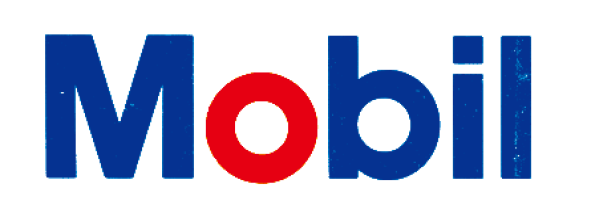
这种字体还被应用在热门电视剧《罗珊娜》的演职员表时,字体的几何形状和粗体设计,显然是要与这个有趣女人的自信、坦率和幽默相呼应。可是,这种表达与拜尔最初的设计意图相距甚远。
通用字体的出现是一种历史现象,它标志着19世纪的文化价值观的崩溃和一个新的、更加"理性"的世界的诞生。历史证明,字体的含义是不断更新的,不受形式的禁锢。例如,在第二次世界大战后,企业采用了不同的通用字体的变体,并合理地运用了拜尔的理性化设计方法,使得企业通过文化构建起来的权威感看上去自然,近乎是一种"事实"。因此,通用字体所具有的意义是由使用者决定的。